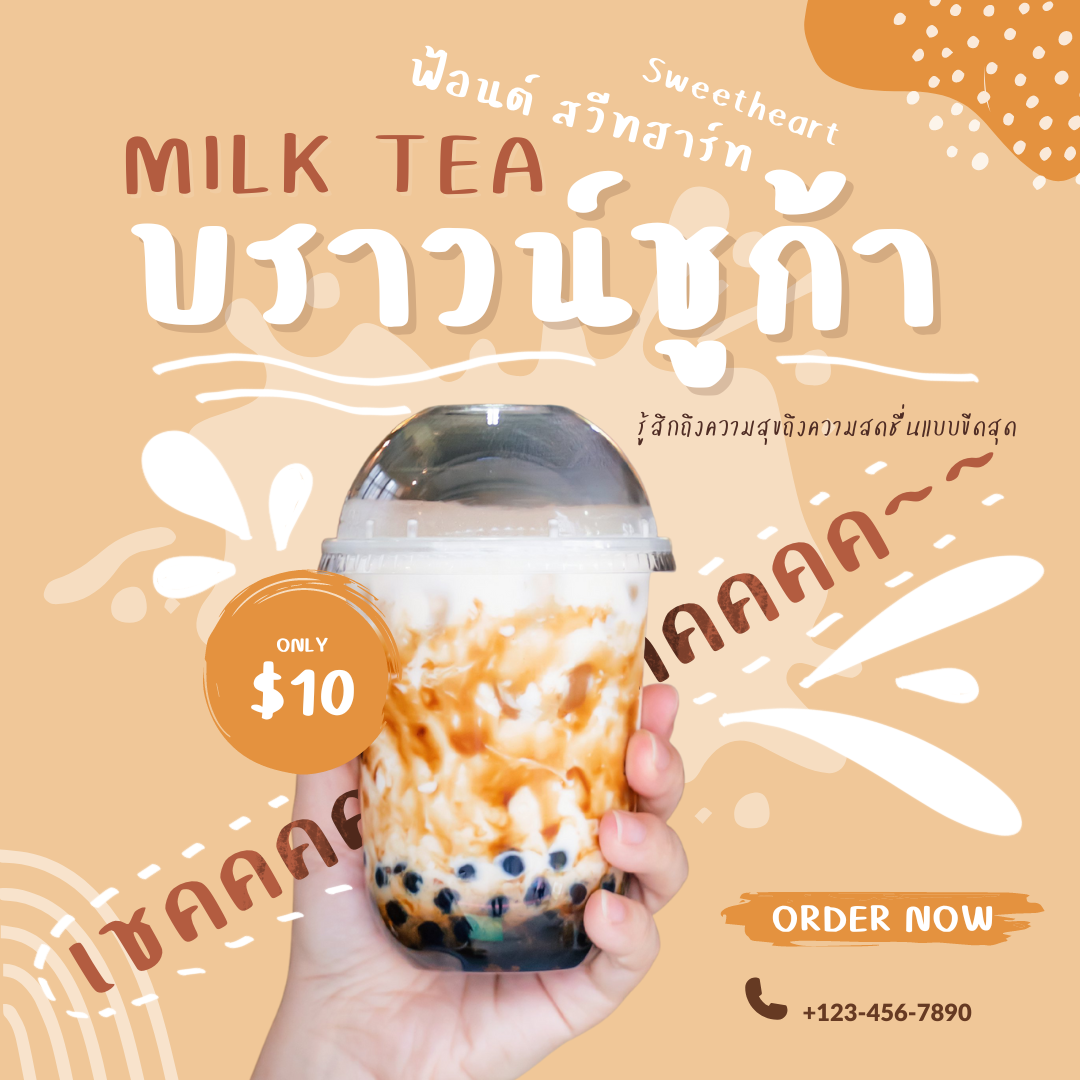
Br-Sweetheart
แรงบันดาลใจในการออกแบบ Br-Sweetheart : นึกถึงฟ้อนท์ตัวหนาๆที่สามารถใช้แล้วเข้ากับพวกน้ำปั่น ไข่มุก เลยกลายเป็นฟ้อนท์ไม่มีหัวเหมาะกับตกแต่งสินค้าของกินให้ดูน่าทานชวนลิ้มลอง และดูน่าสนใจ แนวทางการใช้งานก็ตามรูปที่แนบไปเลยครับ และแจกฟรีไปเลยเวอร์ชั่นทดลอง แบบปกติ  1 สไตล์ ขอให้สนุกกับการใช้ฟ้อนท์ Br-Sweetheart นะครับ  :12: ถ้าอยากได้ 3 สไตล์ก้สนับสนุนได้ช่องทางเชิงพาณิชย์เลยครับ